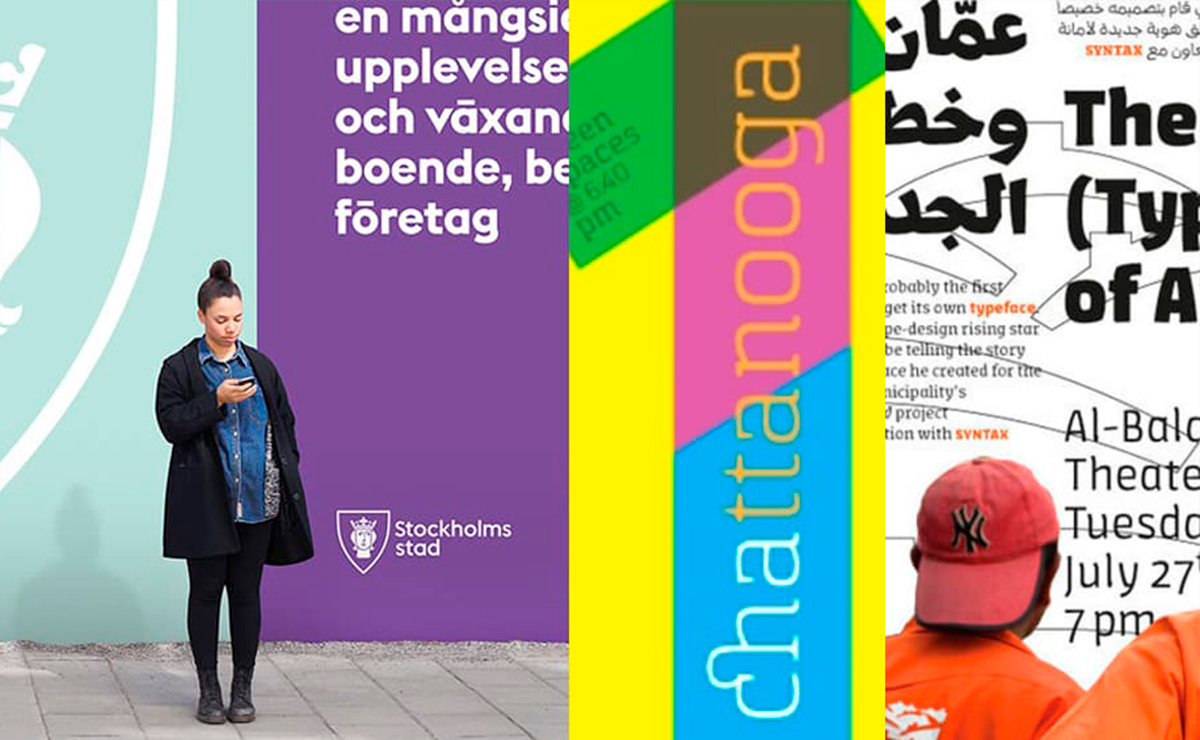
Ciudades con carácter
Hace unos días nos hacíamos eco de la noticia de que Nadine Chahine, gran referente en el diseño de tipografías árabes y tipógrafa de Monotype, había diseñado la tipografía para la ciudad de Dubai.
Nadine ha diseñado el alfabeto árabe y el latino, cubriendo así 23 idiomas distintos. Con esta tipografía Dubai crea una potente herramienta de comunicación que salva la distancia gráfica entre ambas escrituras. Reflejando la peculiar naturaleza de la ciudad-estado y promoviendo su posición global. Aquí puedes descargarte la letra Dubái y ver su historia completa.
A pesar de lo que algunos digan, no es la primera ciudad en tener una tipografía propia. Por ejemplo, a finales de los 90 el Municipio de la Ciudad de Eindhoven (Países Bajos) crea una agencia de diseño virtual donde diferentes agencias competidoras trabajan de la mano para crear la identidad de la ciudad y su carácter. A día de hoy, el resultado puede verse por toda la ciudad.
Otro proyecto similar es el de Berlín que, a raíz de un decreto del Senado en 2007, generan un nuevo posicionamiento de marca para Berlín como ciudad de cambio lanzando un concurso para su campaña estratégica. Alessio Leonardi fue el encargado de diseñar BMFChange para ser la nueva tipografía de la capital alemana. La letra refleja perfectamente, junto con el excelente marco gráfico de la campaña, el carácter de sus habitantes: fuerte, con autoestima, algo tosco y prominente. Un carácter con peculiaridades y con voz propia a través de esta tipografía, los berlineses son los verdaderos protagonistas de esta campaña. Durante el proyecto el alcalde deseó incorporar los elementos gráficos de la campaña en la propia comunicación administrativa, por lo que se hizo una adaptación más condensada y algo más calmada de la tipografía. El éxito ha dado la razón a la campaña be Berlin que ha día de hoy sigue vigente.
Un caso propio de la época 2.0 es el de Chatype, la tipografía de Chattanooga (la cuarta ciudad más grande del estado de Tennessee). Los tipógrafos Jeremy DooleyRobbie De Villiers junto con otros dos socios iniciaron un micromecenazgo en 2012, precedido por una campaña mediática que promovía complementar la identidad de esta gran ciudad con su propio tipo de letra. En tan sólo un mes, consiguieron recaudar los 10.000 dólares requeridos. El resultado es una tipografía de descarga gratuita que recoge las premisas comunicativas marcadas por la ciudad: un carácter dinámico y único que mira hacia el futuro, tecnológicamente fuerte pero sin olvidarse de su herencia cheroqui.
En 2014, el cambio de identidad de Estocolmo marca un antes y un después rotundo que rompe con el pasado de esta ciudad. EssenInternational se encargó de crear una tipografía específica tanto para la marca como sus aplicaciones, que personaliza de una forma muy potente la renovación de la ciudad. El gran reto de este proyecto consistía en unificar todos los organismos, empresas, servicios y eventos bajo una misma marca y lenguaje, empezando por las administraciones hasta los eventos más punteros de la ciudad, como por ejemplo el Festival de Cultura de la Estocolmo. La aplicación de la marca y tipografía es consecuente y bien visible en todas las comunicaciones gráficas, incluyendo la web (cosa que se echa de menos en otras tipografías municipales). La capital sueca logra así hablar con una sola voz en todas sus comunicaciones en un tono moderno, fresco y limpio posicionándose como ciudad referente, progresista y dinámica.
Otra tipografía que, a pesar de no haber sido fruto de un encargo o concurso, se ha convertido la esencia de la capital Jordana. Este es el caso de la letra FF Amman Sans diseñada por Yanone que desarrolla las tipografías como parte de su proyecto de graduación en la Universidad Bauhaus (Weimar, Alemania). La familia se compone de siete sans serif y cuatro pesos serif, cada uno con sus cursivas árabes reales, y conjuntos de caracteres latinos y árabes completos. Yanone planteó un rediseño de la imagen con motivo de la celebración del Centerio suponiendo una especie de regalo de cumpleaños para Amman, cuyo resultado fue ampliamente adoptado para ser utilizado en sus servicios municipales.
La identidad de una ciudad está íntimamente ligada a la tipografía. Todo aquello que vemos desde que salimos de casa hasta que volvemos marca su personalidad, especialmente lo que perdura en el paso del tiempo. Por eso, el sistema de transporte público, los rótulos y los letreros de las calles definen el carácter vernáculo de las ciudades. Un claro ejemplo es la tipografía Johnston Sans o la Gill Sans en Londres. O la Gotham en Nueva York, así mismo la Helvetica también ha estado siempre muy ligada a esta metrópolis por ser el tipo de letra de su metro aunque, ante todo, Helvetica representa no sólo la personalidad de una ciudad sino todo el lenguaje gráfico de un país entero: Suiza.
Una bonito ejemplo ibérico de letraje vernáculo hecho tipografía es el de la Granaina, diseñada a partir de la cerámica de las calles de Granada por Vanesa Aguilera y Sergio Arredondo.
Y no sólo están las tipografías que dotan de voz a las ciudades, sino también infinidad de ciudades que ponen nombre a tipografías precisamente por esa historia y esos valores que asociamos con cada lugar. Cuenta Susana Kare que cuando diseñaron las primeras tipografías para Macintosh nombraron las fuentes por ciudades en las que paraba una línea local de tren. Fue Steve Jobs quien intervino para que las ciudades elegidas fueran sustituidas por ciudades de “clase mundial”. Chicago se convirtió en icono pop como fuente del sistema operativo, Monaco fue la primera fuente monoespaciada con la que nos familiarizamos y no en vano Geneva lleva nombre de ciudad suiza al imitar a las primeras creaciones tipográficas de estilo suizo como Helvetica y Univers.
También en Bauertypes, tenemos en su catálogo Neufville Digital una tipografía con un nombre de ciudad: Paris ND. Una de las tipografías de la colección de Grafía Latina de Enric Crous-Vidal.
La tipografía forma parte de la vida cotidiana de los ciudadanos que no identifican activamente lo que ven, pero sí forman parte de la cultura gráfica que les rodea. Una tipografía no es capaz de posicionar a una ciudad en lugar que no le corresponde o en una posición que no está. Pero una tipografía sí es capaz de reflejar la personalidad de una ciudad y de su gente, hacia dónde se dirige, qué aspira ser o su carácter particular. La tipografía, como hemos visto, representa la voz gráfica y marca el tono de comunicación. Es la forma en la que una ciudad habla a sus ciudadanos, los visitantes y la comunidad internacional. Por lo tanto una tipografía puede encarnar, promover y complementar la identidad de una gran ciudad.
Como estrategia comunicativa o de posicionamiento, una tipografía a medida o personalizada que refleje los valores de una ciudad es un arma de identidad masiva. Encontrar la voz que hable el idioma o jerga de una ciudad es una apuesta segura. El rango de posibilidades es muy amplio: desde una tipografía creada desde cero, a partir de un briefing e incluso la customización de una ya existente afín a nuestros valores (haciendo los ajustes pertinentes de glifos y cambiándola el nombre).
¡Todos queremos vivir en una ciudad con carácter!